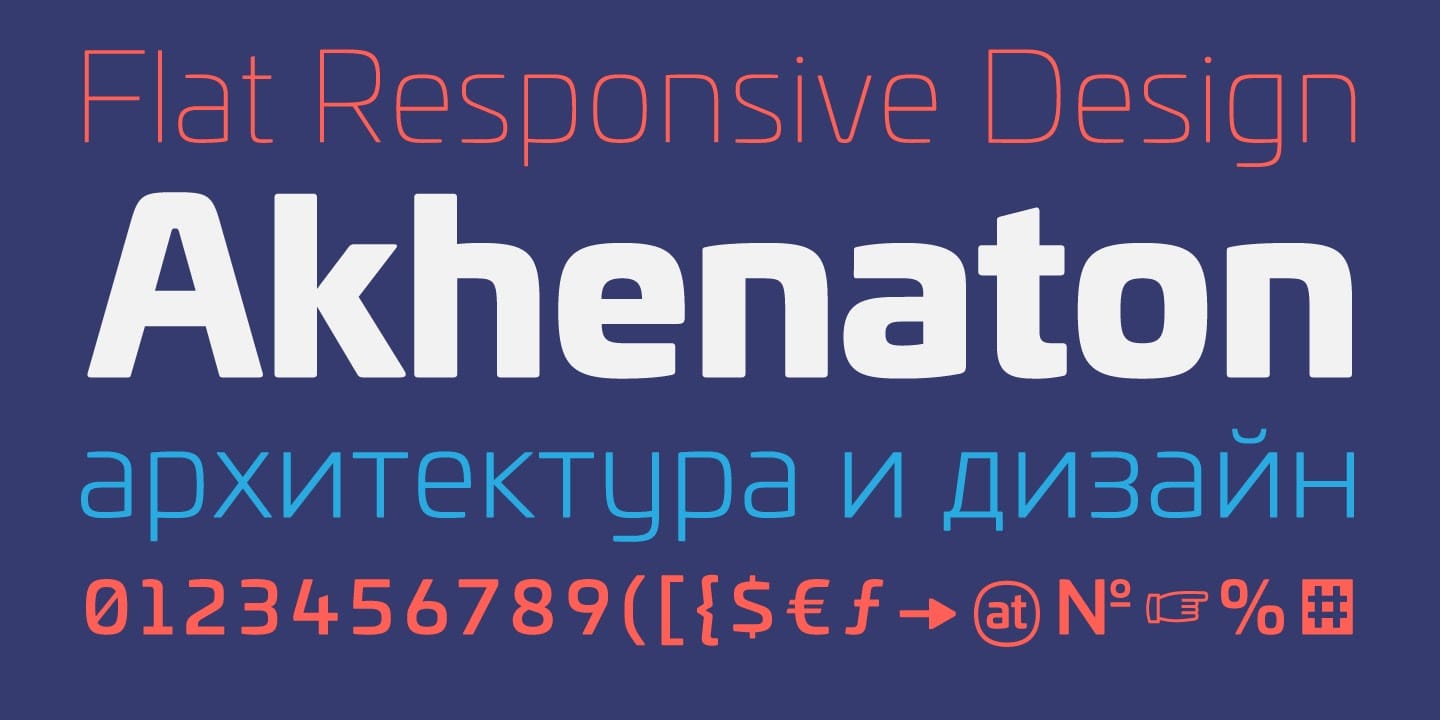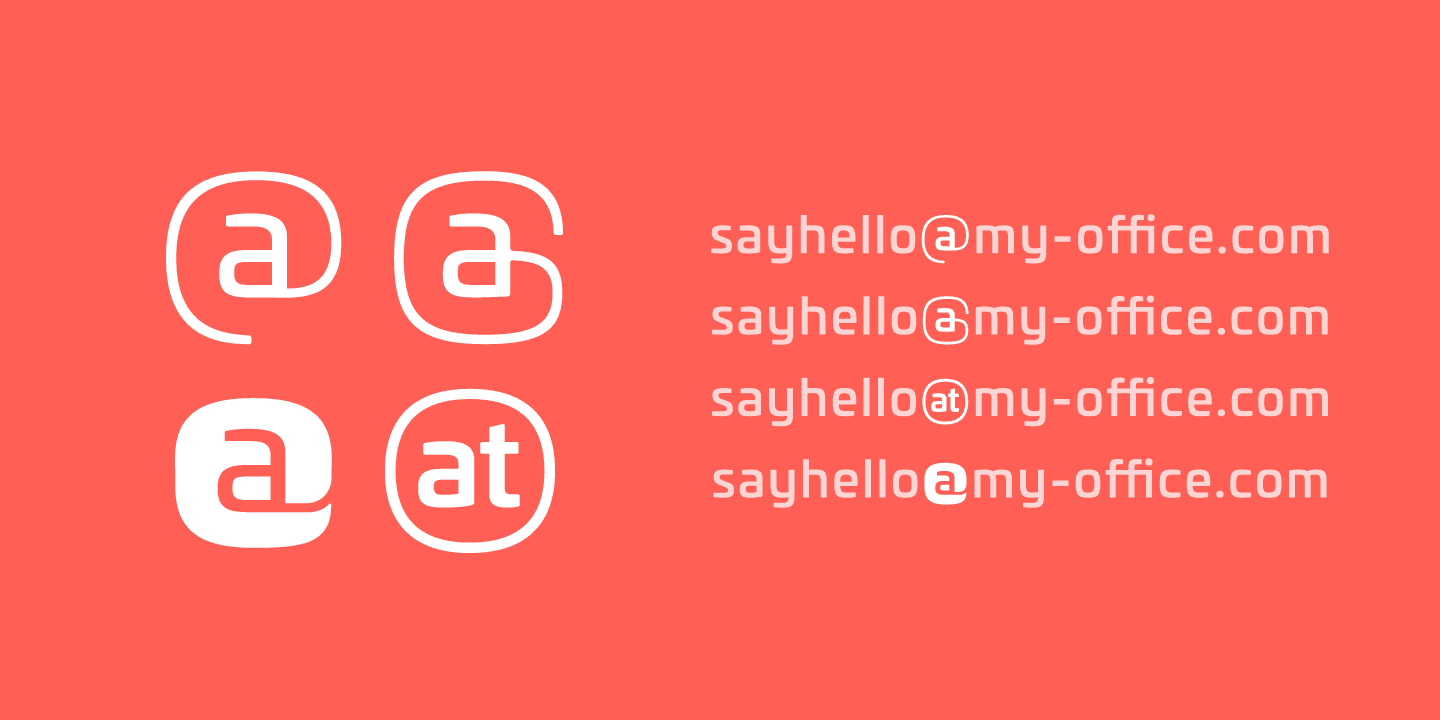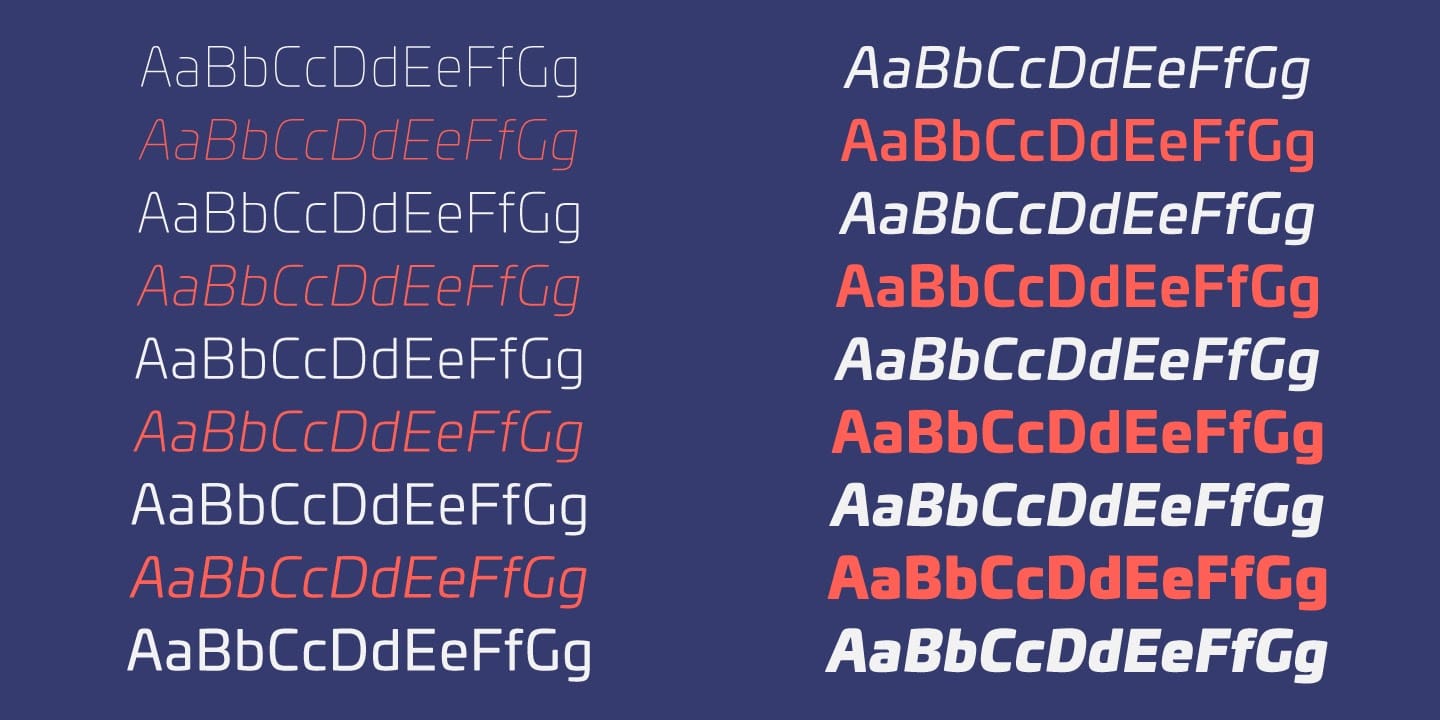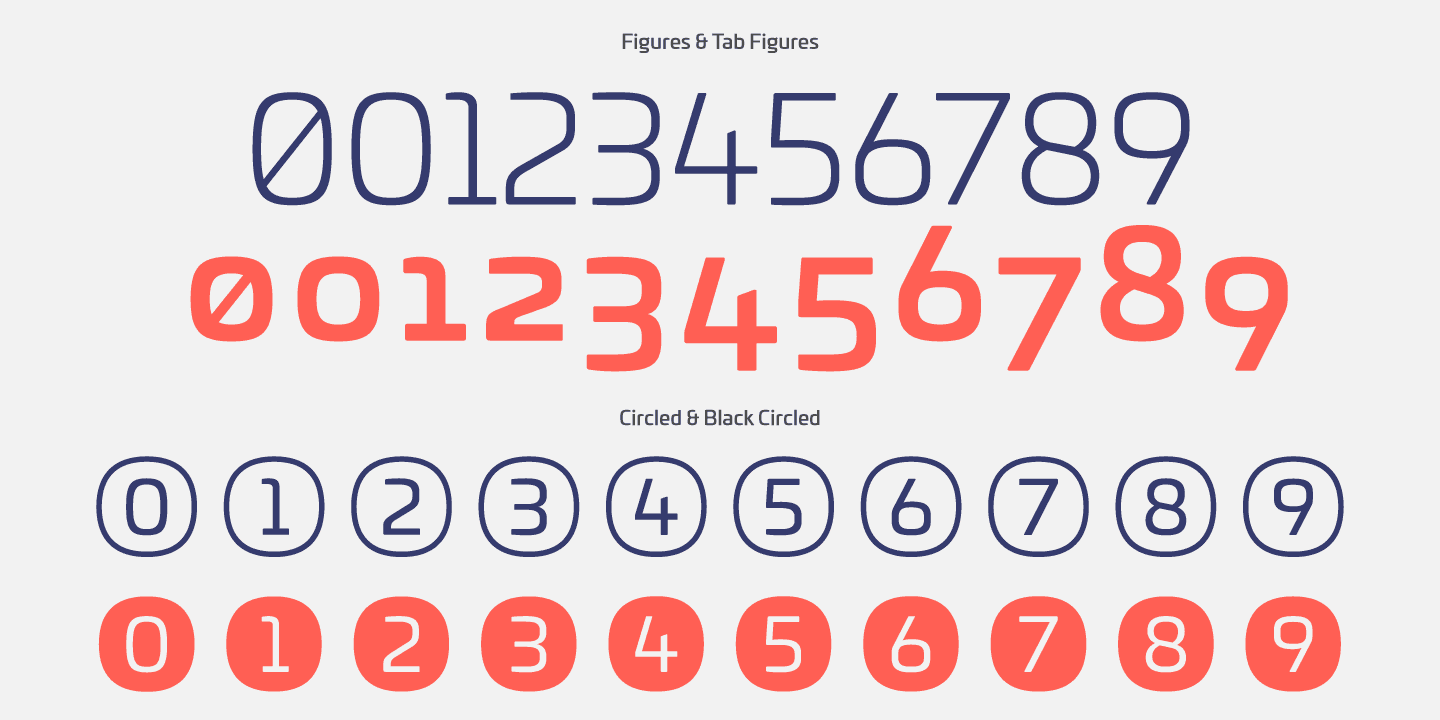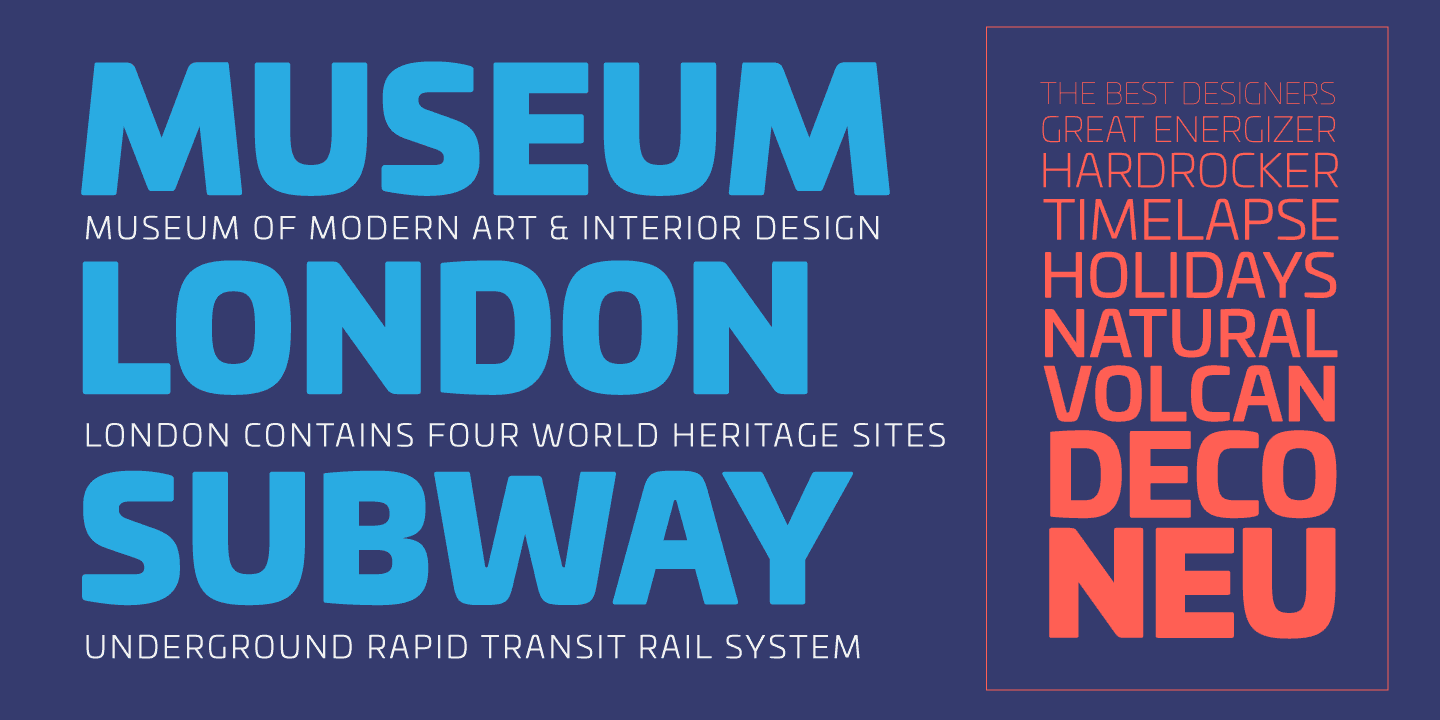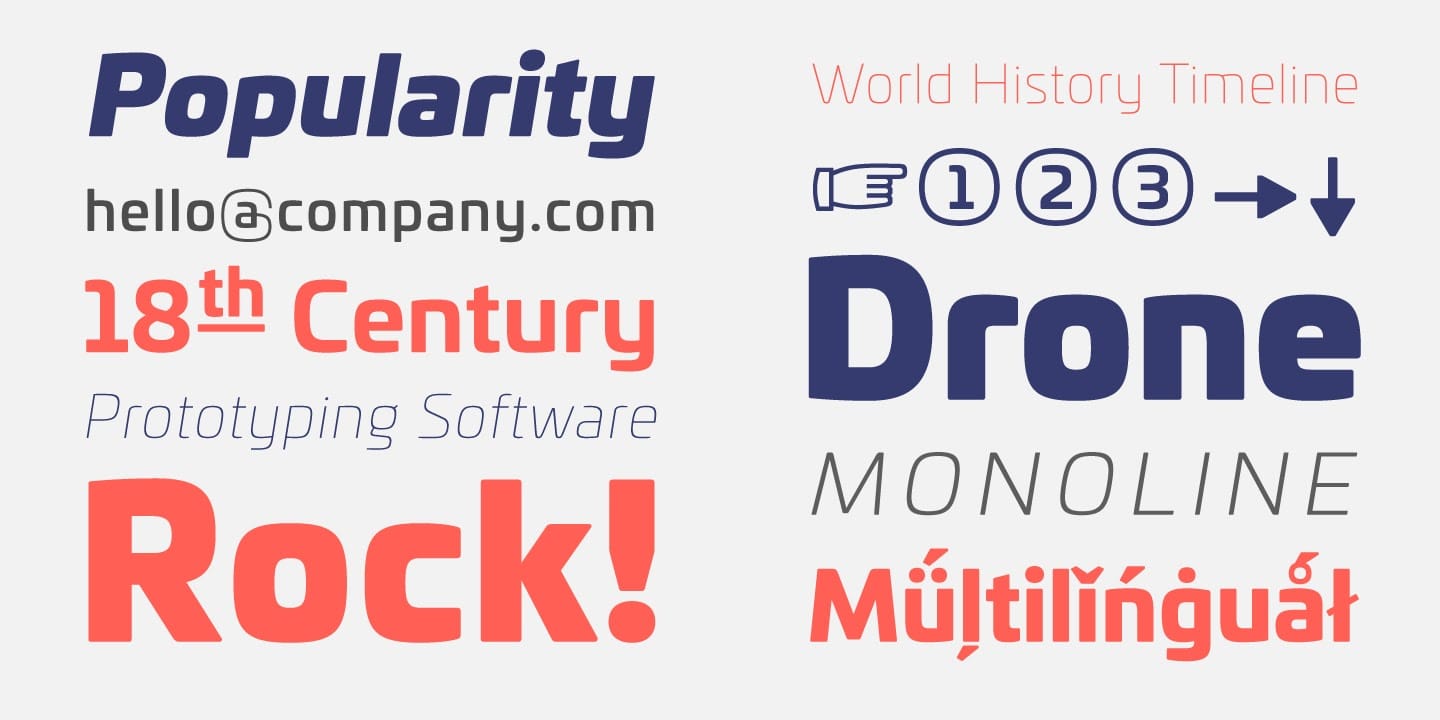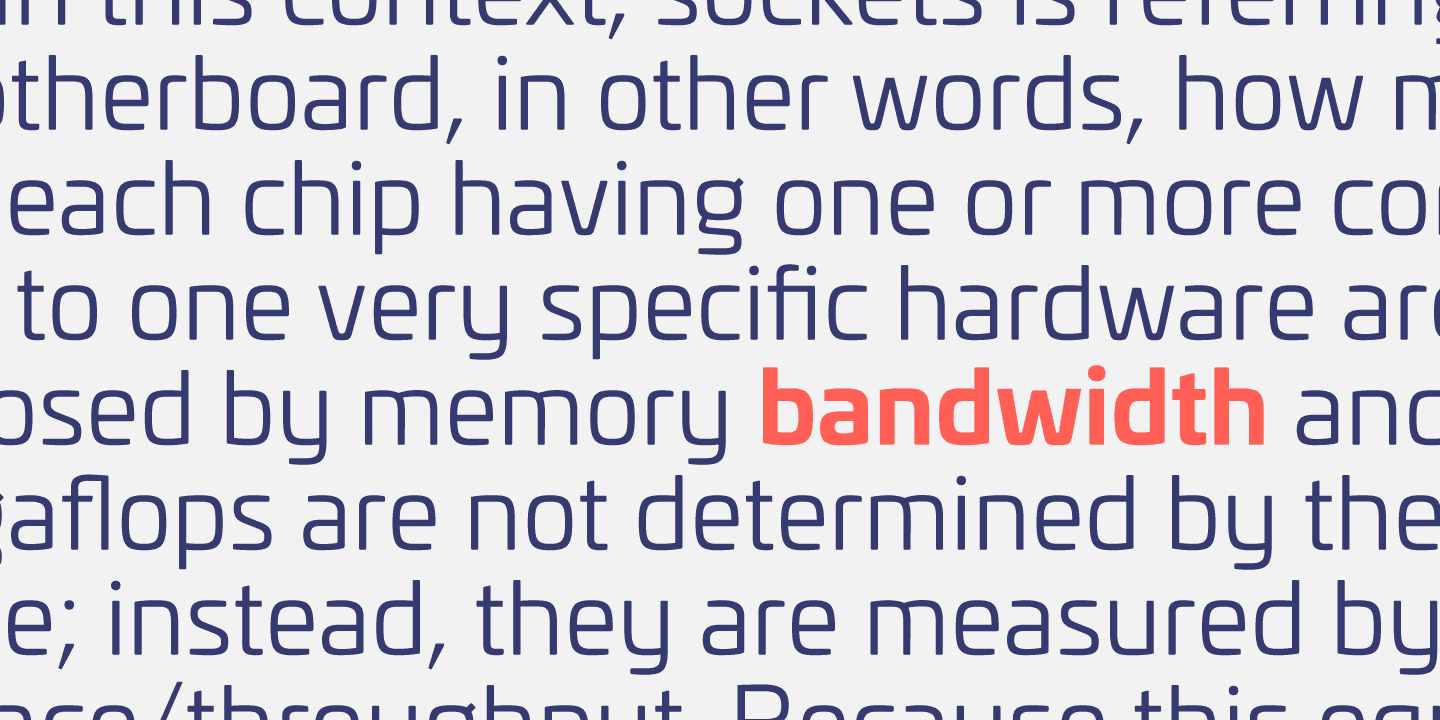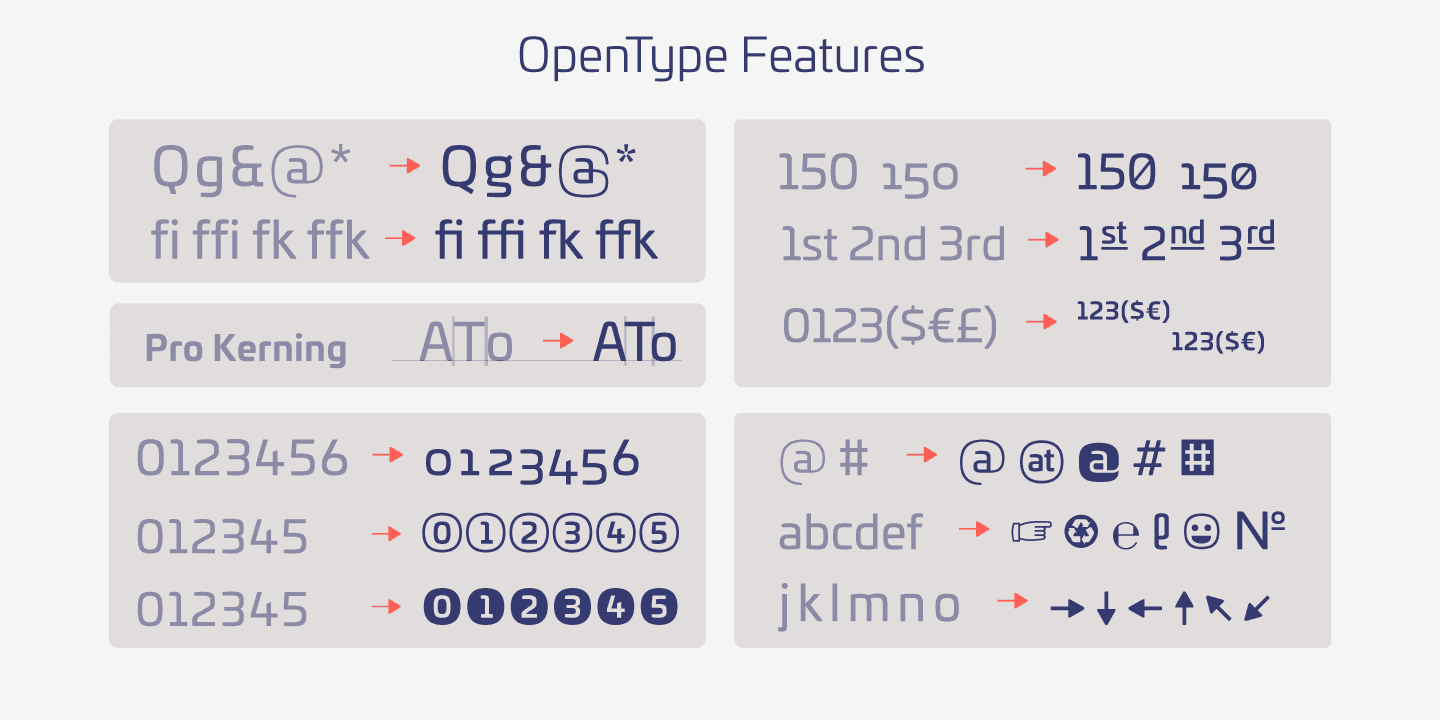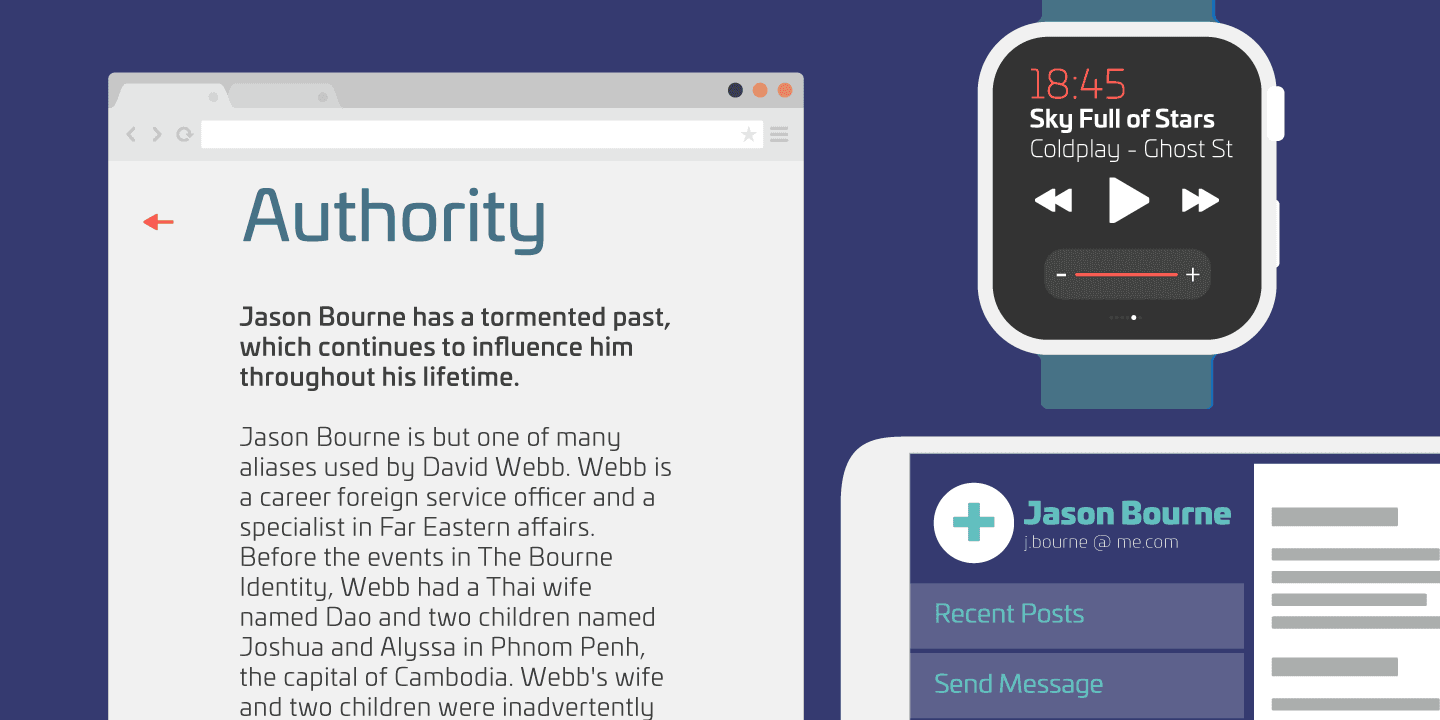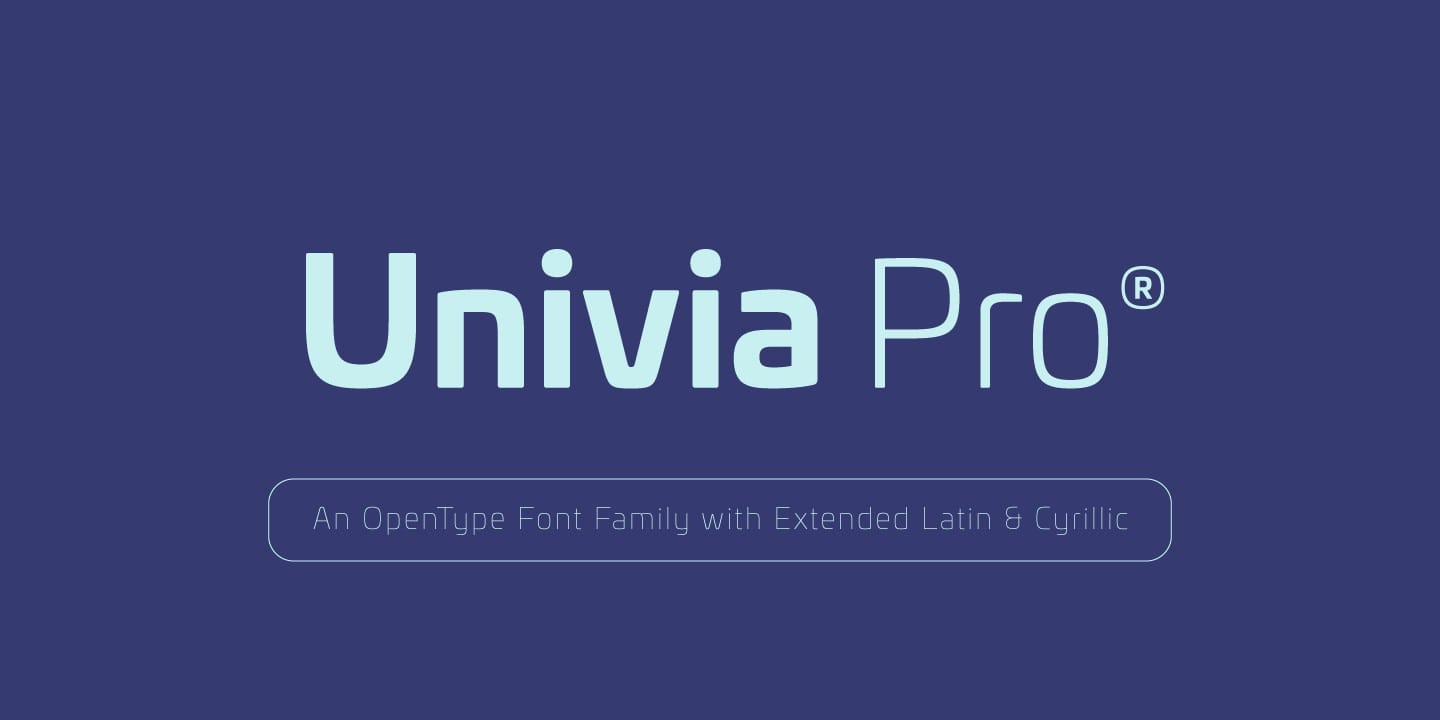
Trọn bộ font Univia Pro miễn phí (18 font) Được thiết kế bởi Olivier Gourvat vào tháng 12/2015, Univia Pro là bộ phông chữ OpenType đương đại mới với tính hiện đại và linh hoạt. Khác biệt với vẻ ngoài dễ chịu và cực kỳ hiện đại, Univia Pro có rất nhiều cá tính chủ yếu đạt được bởi các đường cong mượt mà và các góc tròn tạo thành một phong cách rất giống nhau.
Univia Pro hoàn hảo cho cả hiển thị và sử dụng văn bản và do giao diện cực kỳ hiện đại, nó còn tuyệt vời hơn cho sách điện tử, trang web, phông chữ giao diện người dùng, ứng dụng di động, v.v. Bộ font chữ cung cấp 18 kiểu khác nhau (9 weights plus italics): Thin, Thin Italic, Ultra Light, Ultra Light Italic, Light, Light Italic Book, Book Italic, Regular, Regular Italic, Bold, Bold Italic, Black, Black Italic, Ultra và Ultra Italic.
Univia Pro hỗ trợ các ngôn ngữ Latinh, Latinh mở rộng và Cyrillic.